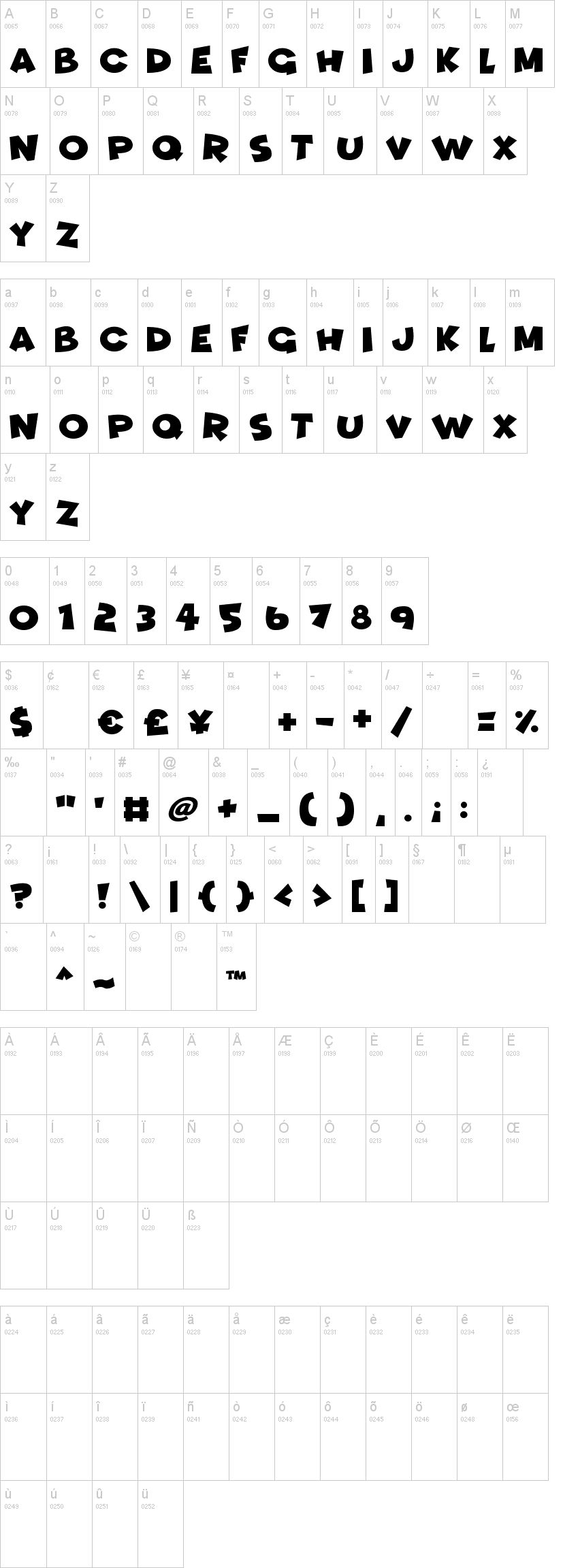
Funhouse
Funhouse 是一种带有装饰性元素的字体,它的设计灵感来自于马戏团和庆典的氛围。这种字体采用了大胆的线条和弧形,强调了它的视觉特点。Funhouse 字体常用于海报、音乐专辑封面、广告和儿童书籍中,以增加视觉吸引力和趣味性。除了常规字母和数字,Funhouse 字体还包括一些特殊字符和符号,如星星、心形和气球等,以提供更多的装饰性选项。总的来说,Funhouse 字体是一种非常有趣和富有创意的字体,适用于需要增强视觉吸引力和趣味性的设计项目。
Funhouse是一款非常不错的手写艺术字体,具有很好的视觉感,适合于文化类的宣传设计、商业类品牌的广告和产品包装设计以及个性化文字排版等较多场景。
Funhouse字符映射图